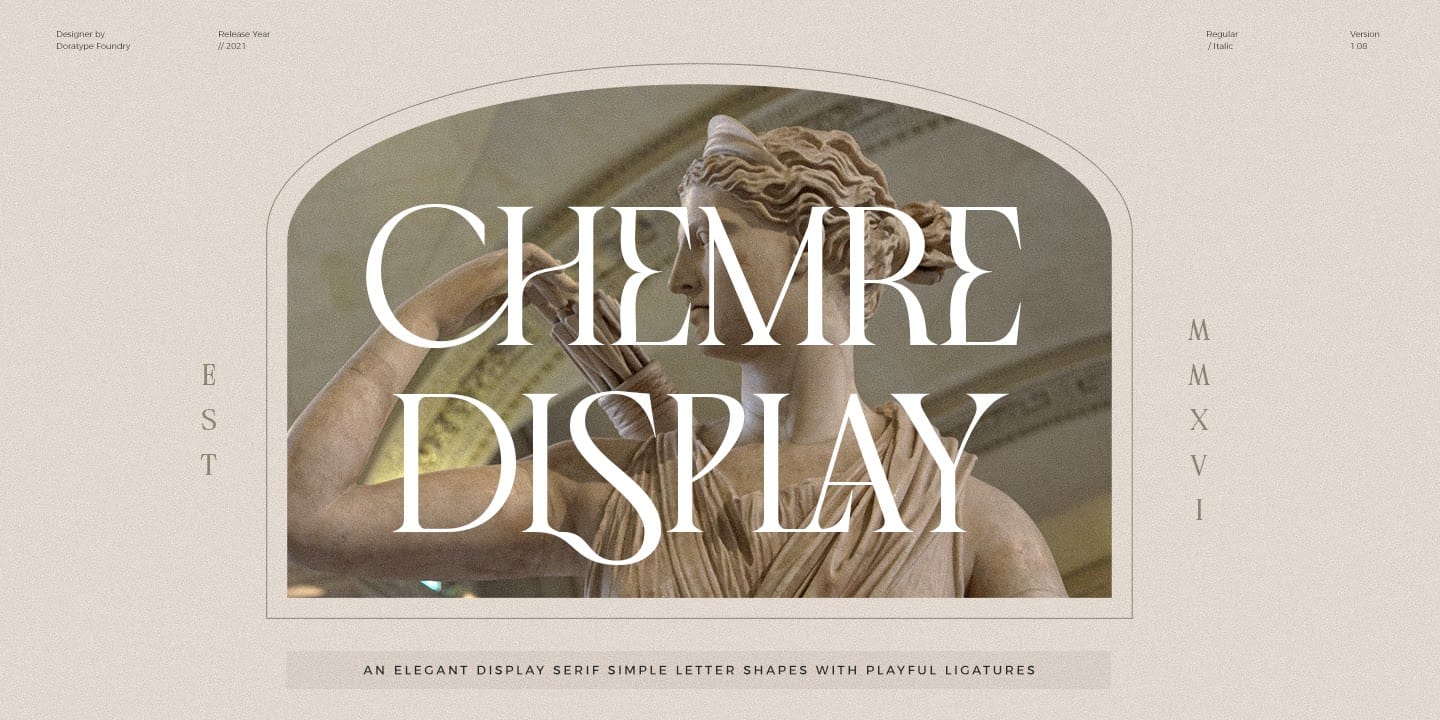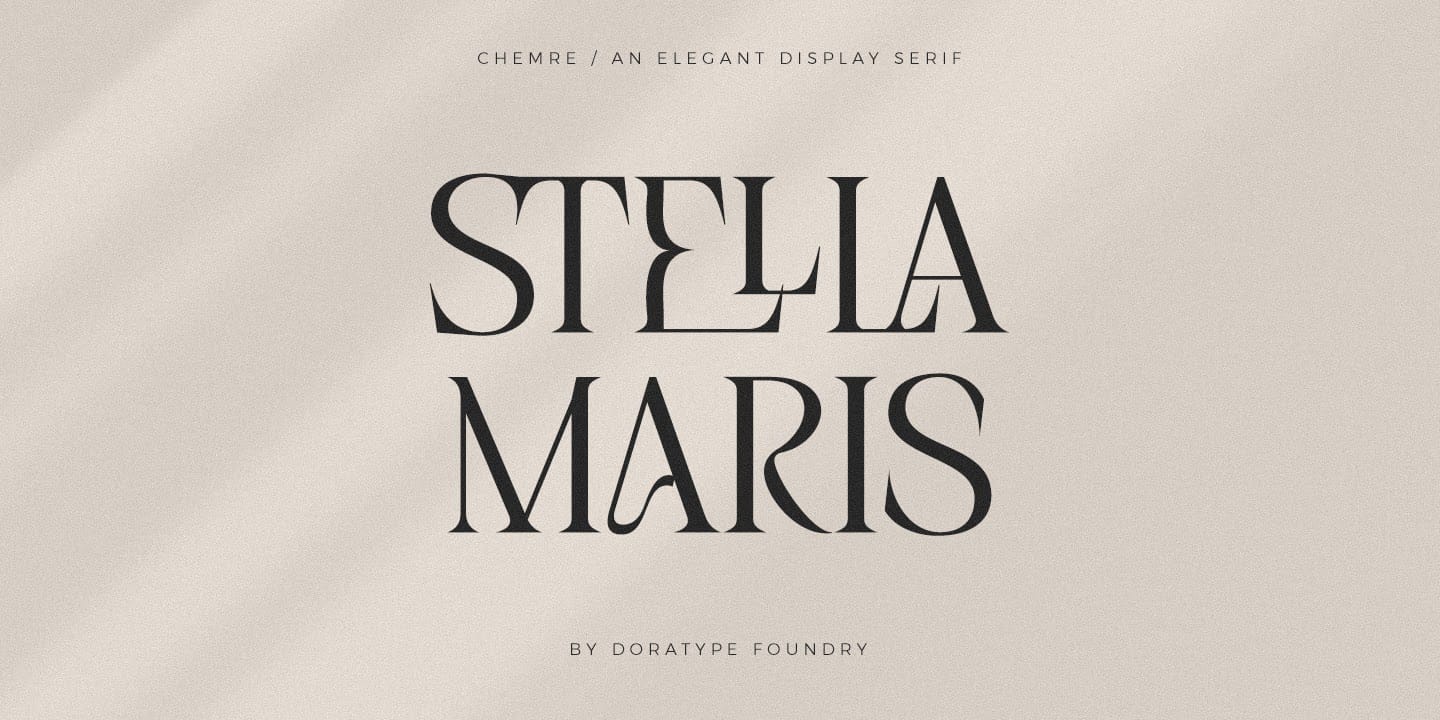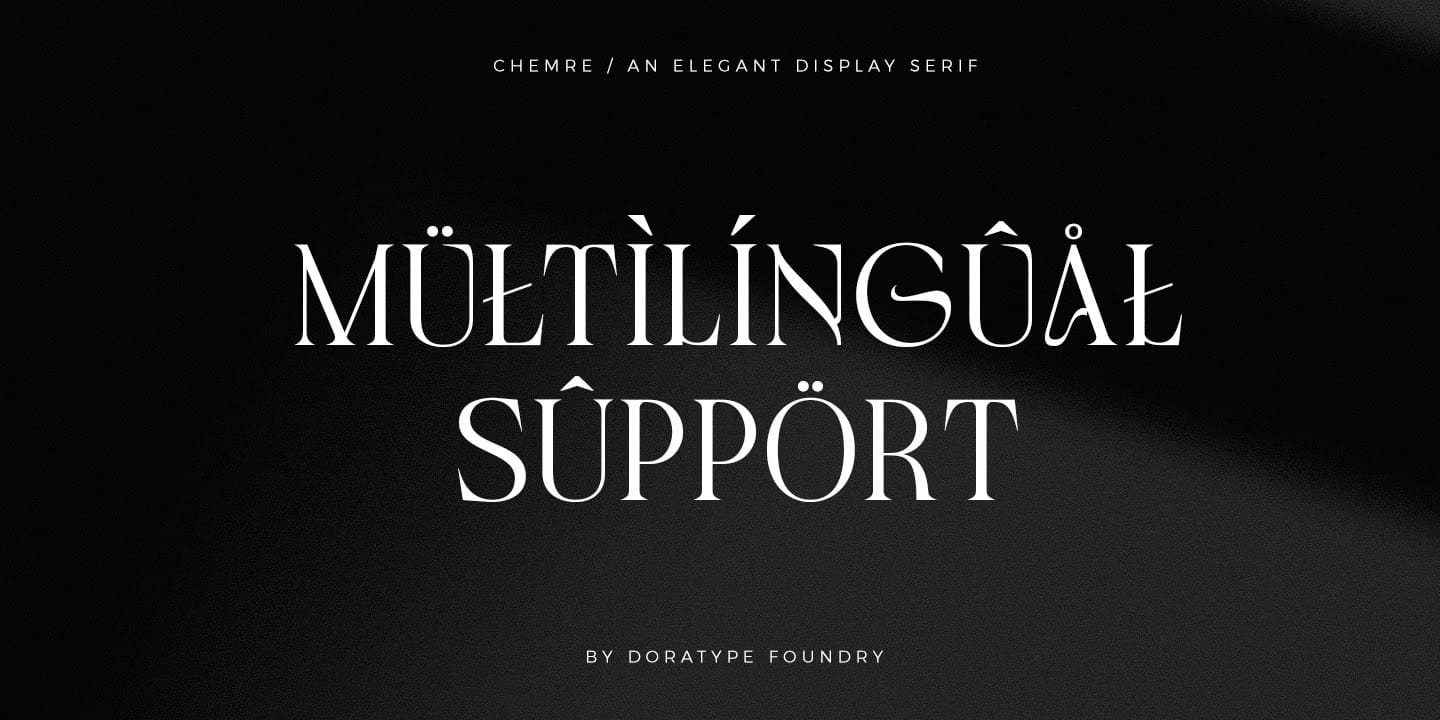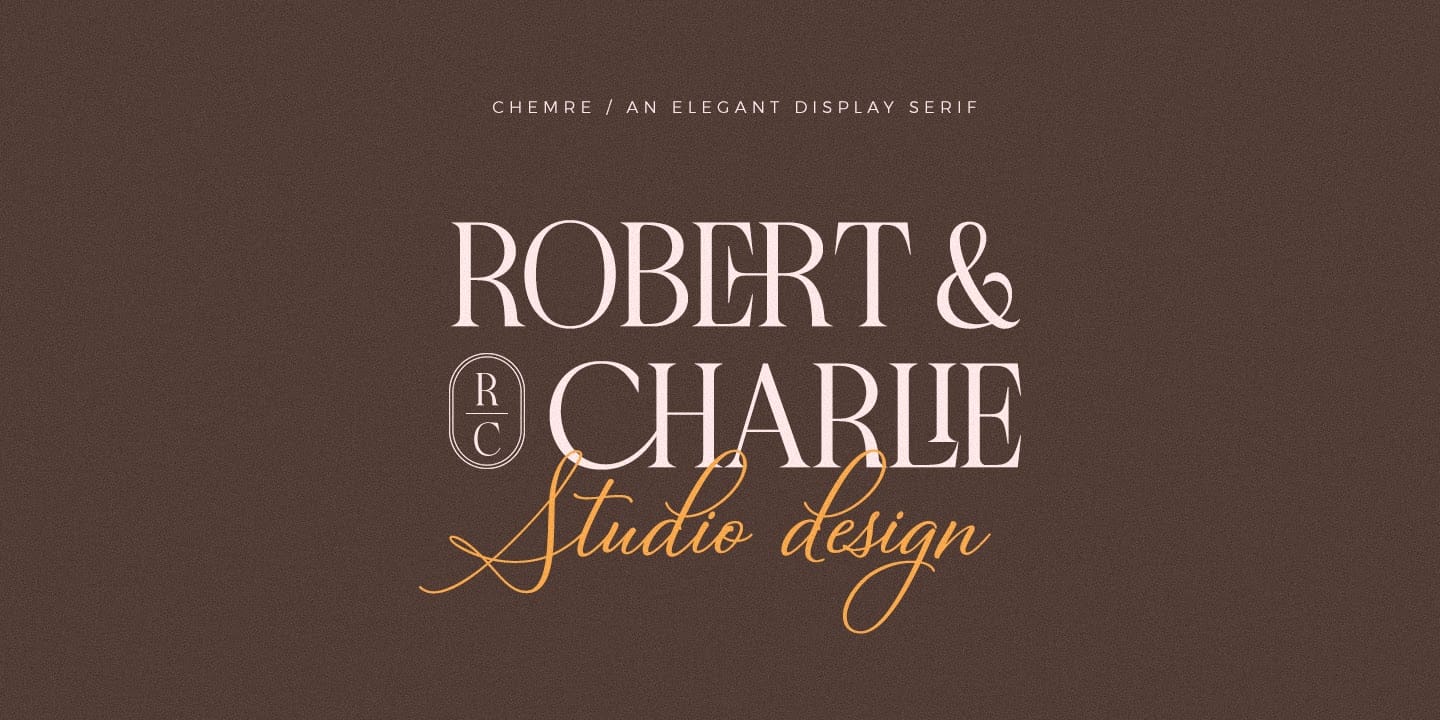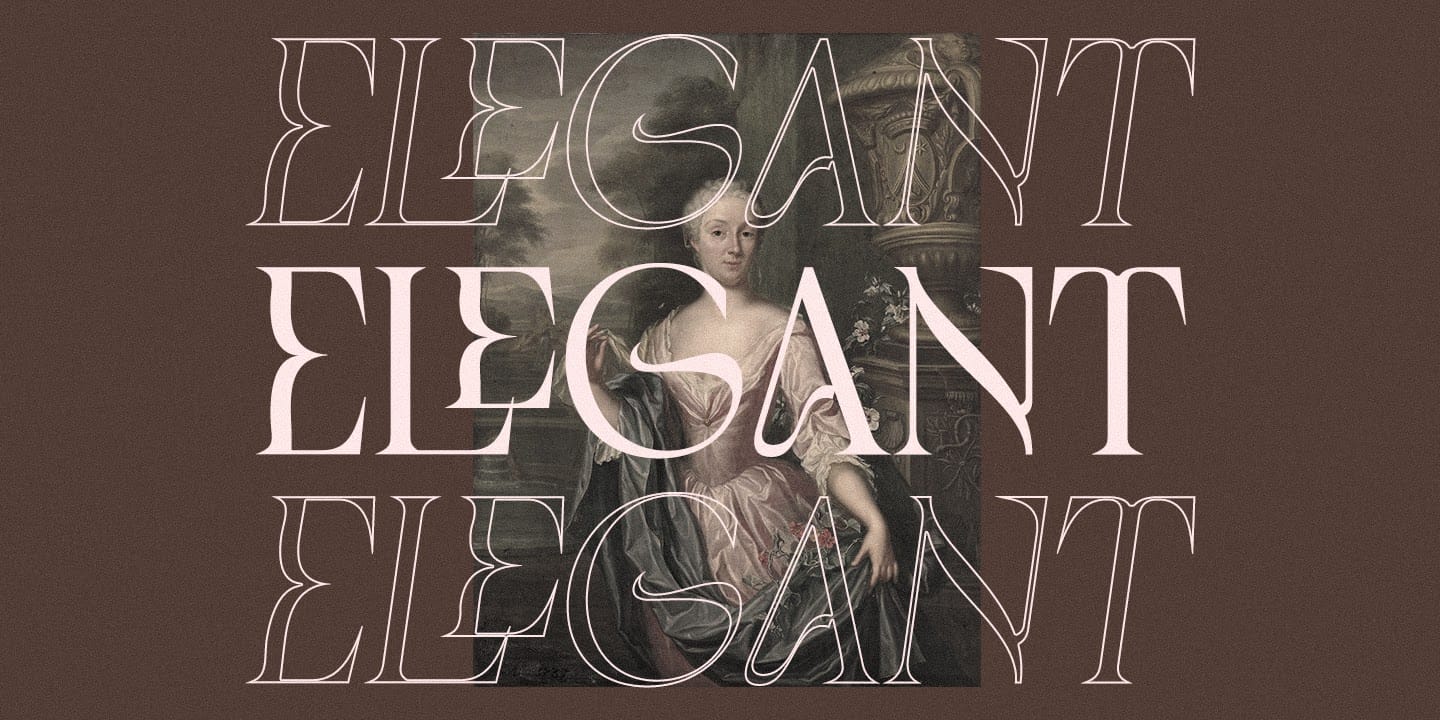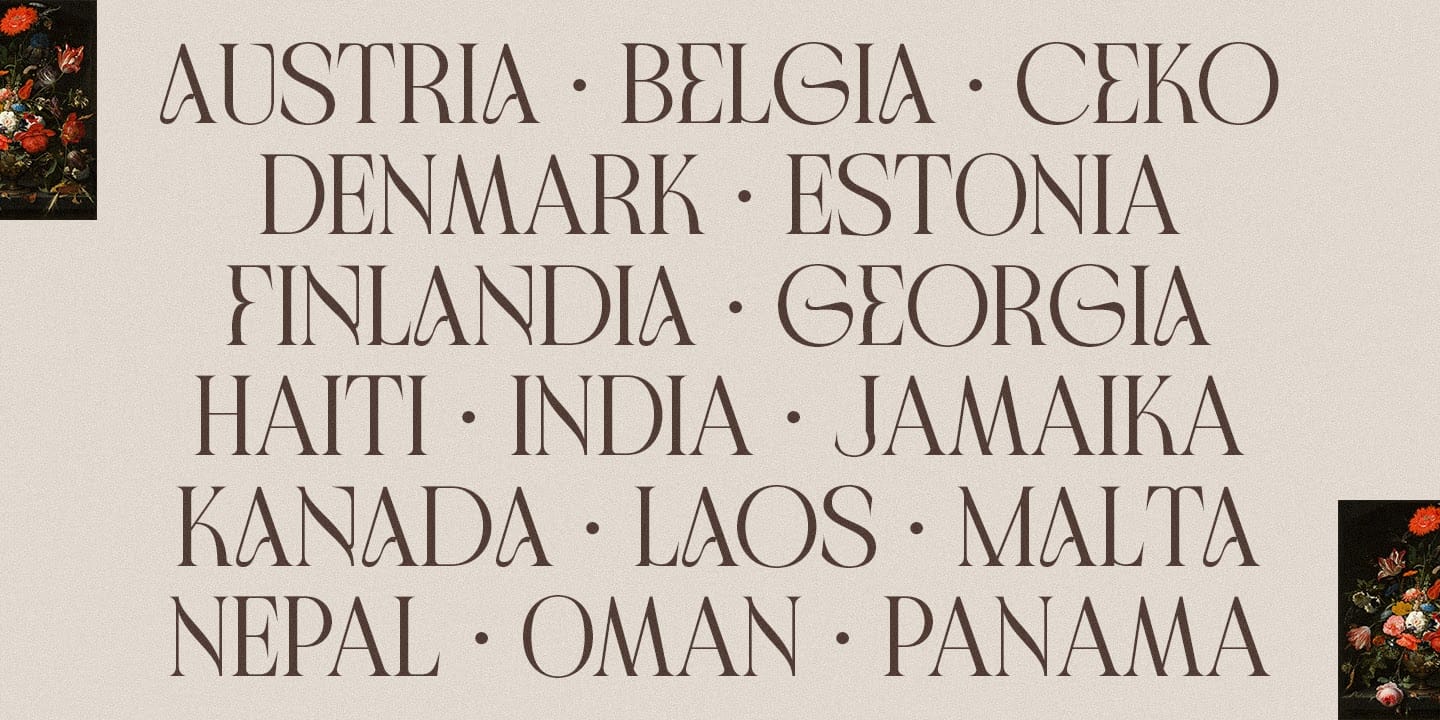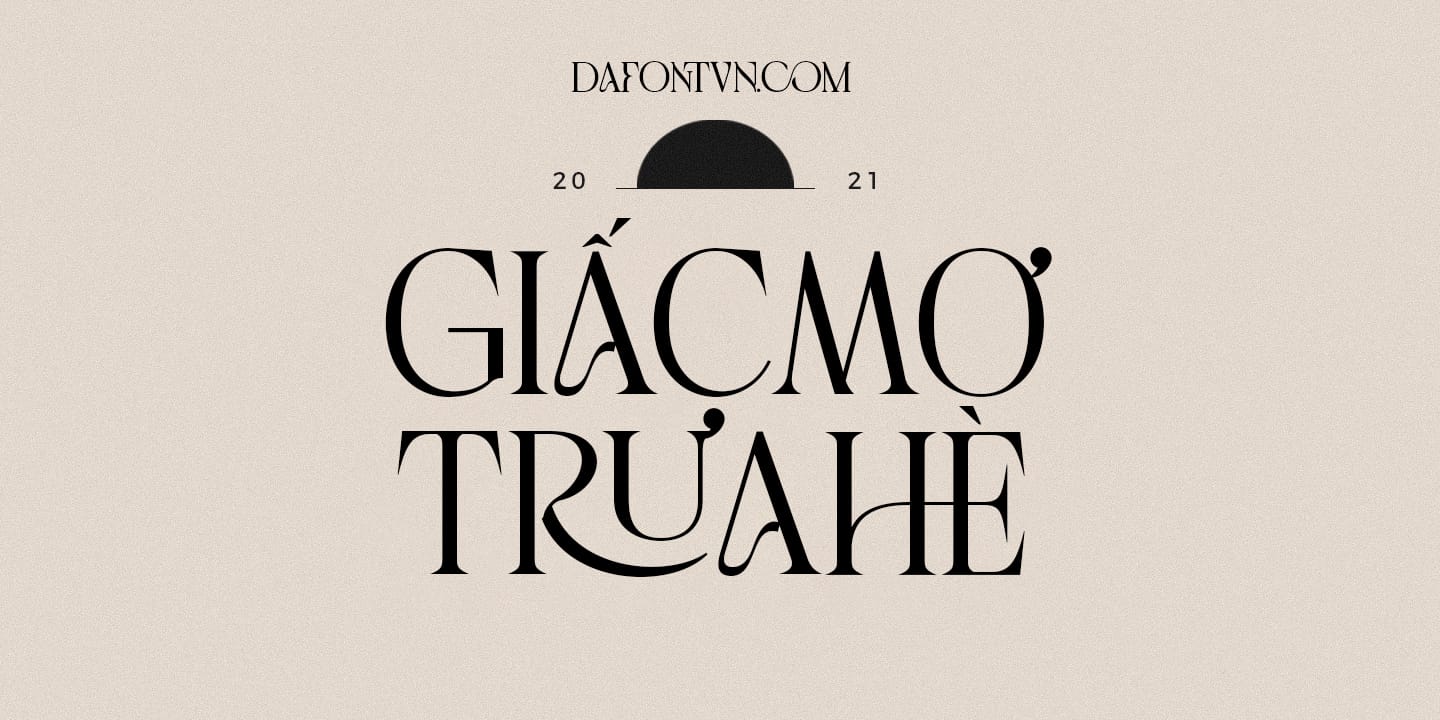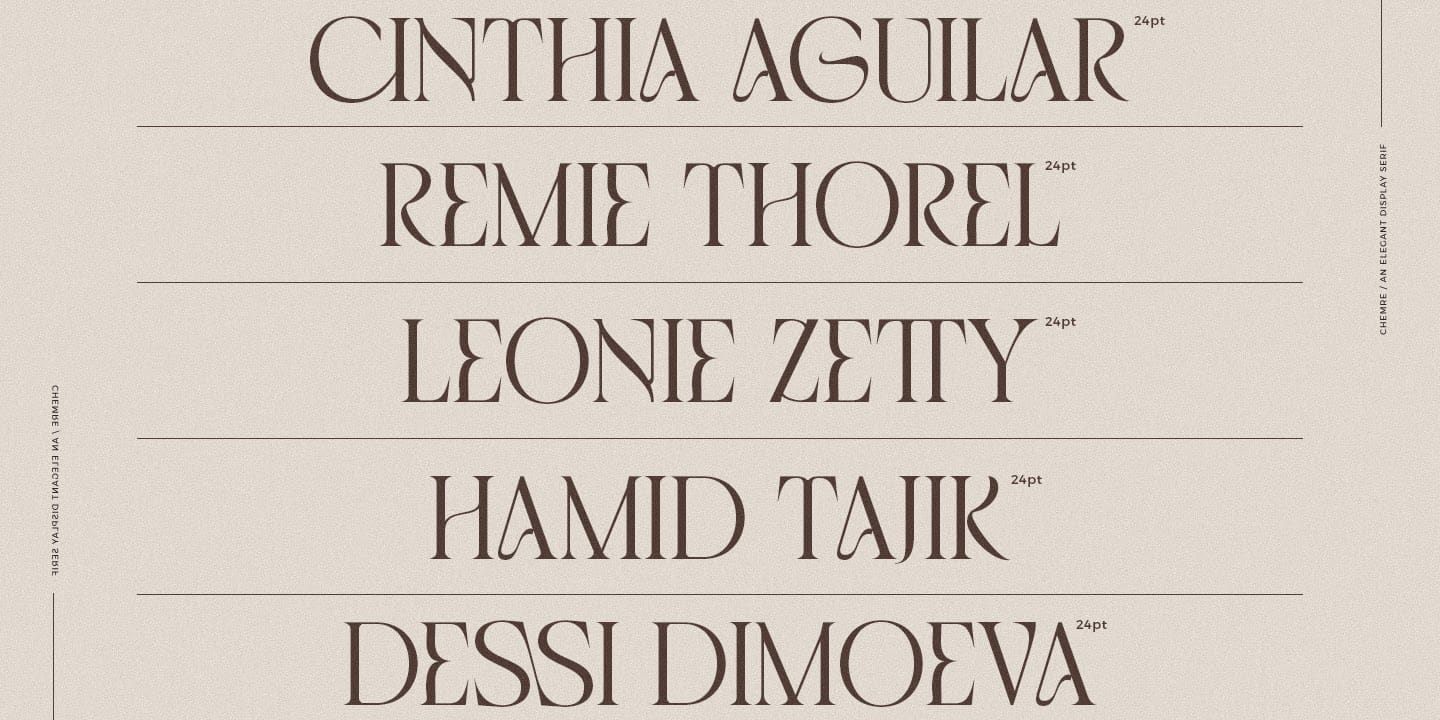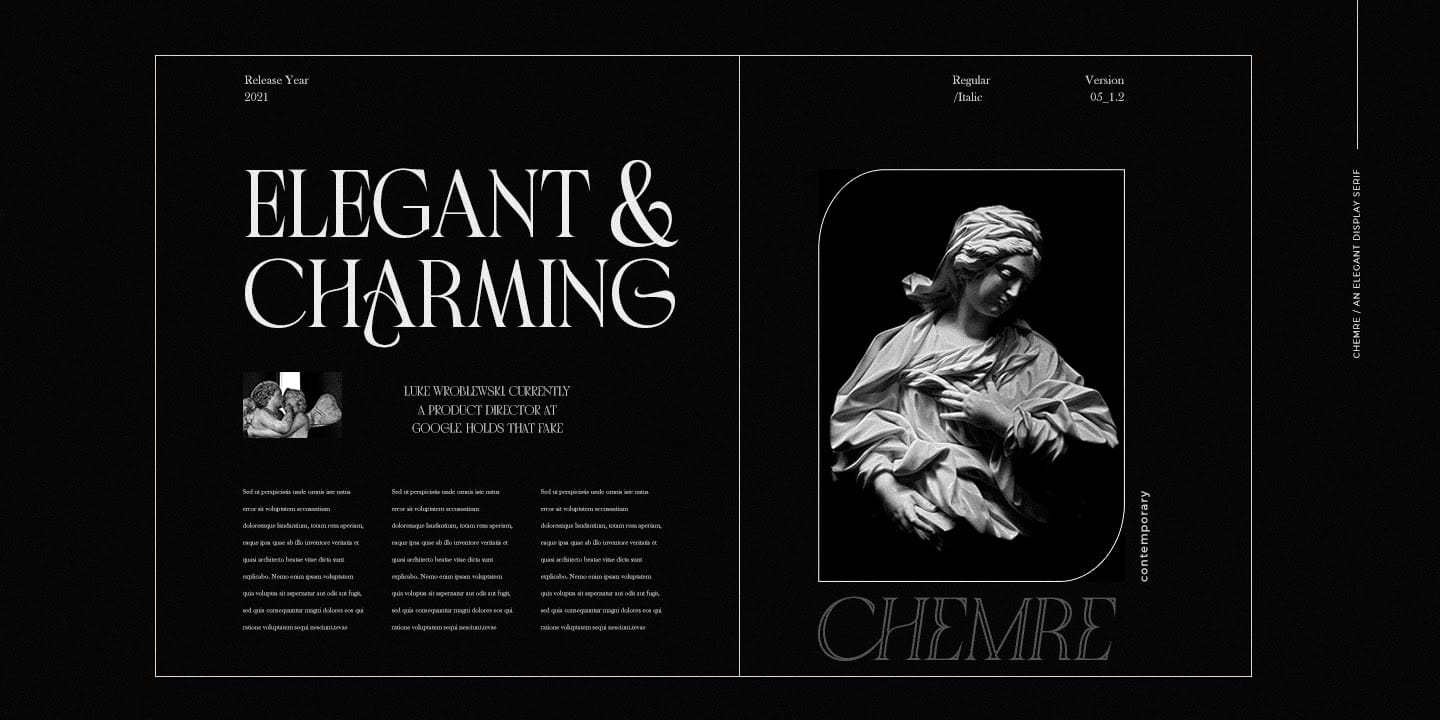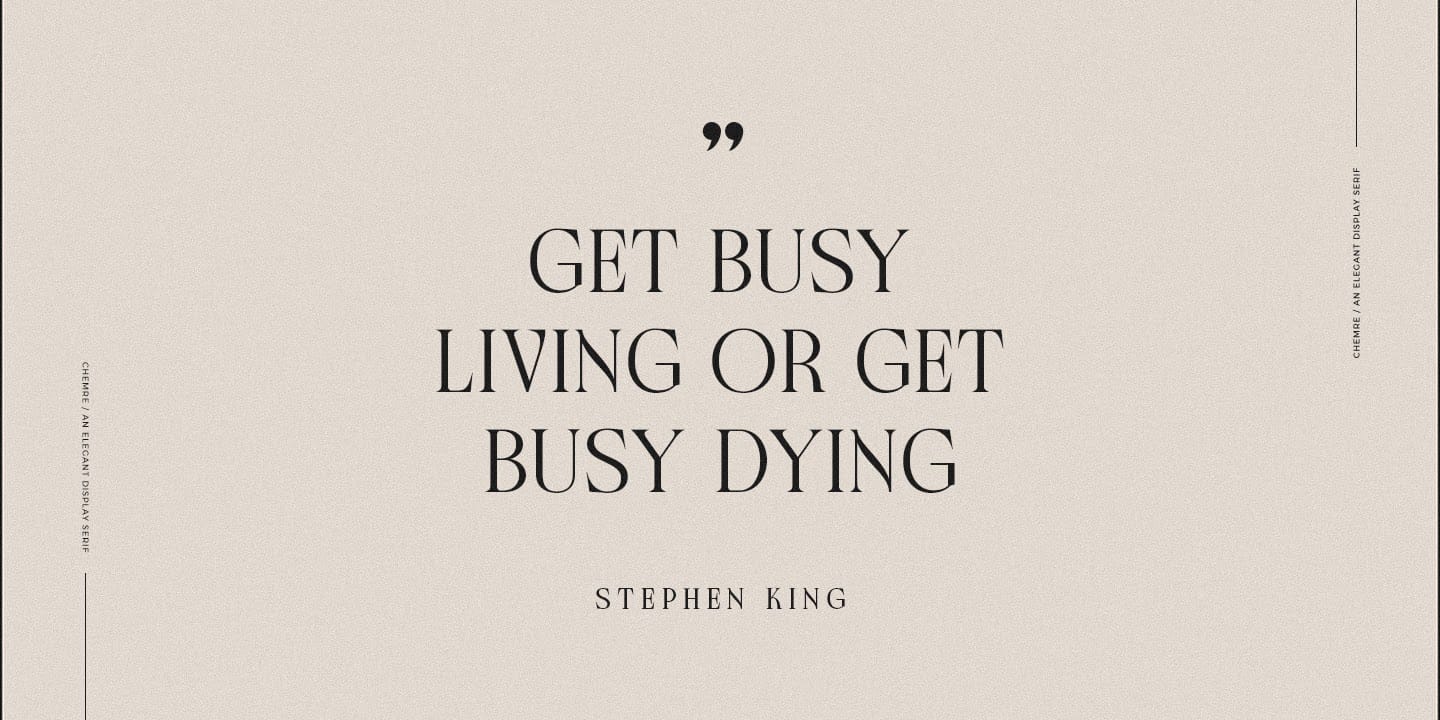
Chemre Font – Một font chữ đẹp và ấn tượng
Chemre là một font chữ serif với thiết kế hiện đại và sang trọng. Font chữ này được bổ sung với sự kết hợp của tất cả các chữ hoa có cùng chiều cao và cho phép kết hợp không giới hạn để tạo phong cách độc đáo cho kiểu chữ của bạn. Độ tương phản cao giữa nét dày và nét mỏng mang lại cho Chemre vẻ sang trọng. Font chữ này có hai kiểu Regular và Italic. Chemre thích hợp cho áp phích, bao bì, thương hiệu, biểu trưng, tiêu đề và thiết kế biên tập.